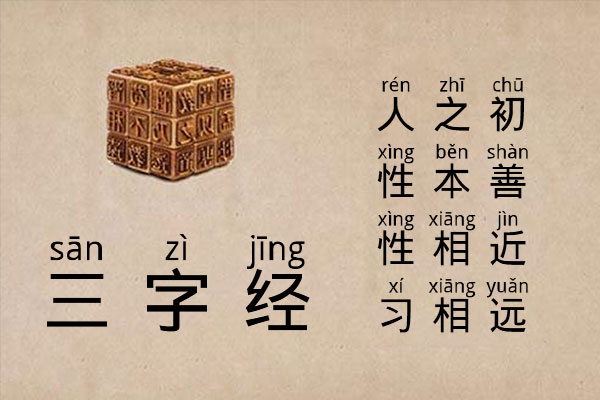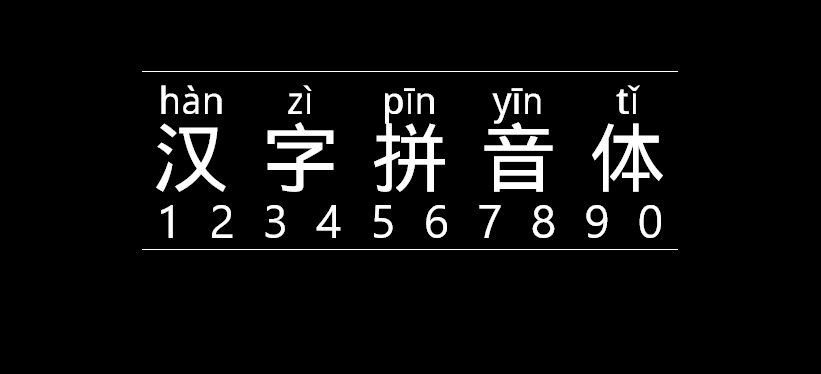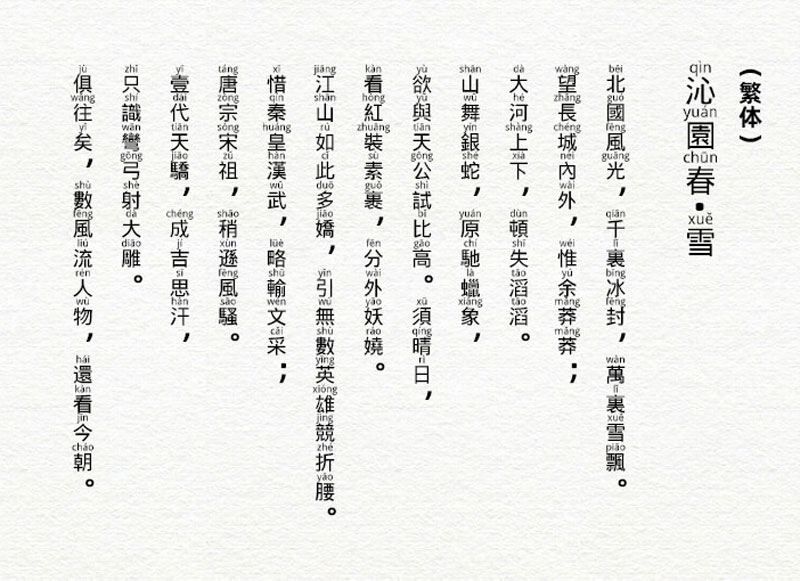
汉字拼音体
汉字拼音体(Hanzi-Pinyin-Font Regular)是一款比较特别的字体,这款字体的文字头上自带拼音。 这是一种用来帮助学生更快地学习和阅读汉语的字体。在某些设计场景其实也挺实用的,特别是对教育类的设计比较有用。该字体简体繁体都支持得挺好的。 汉字拼音体是遵循CC-BY-SA-4.0授权协议,可以免费用于商业用途、发布,修改,私用等。